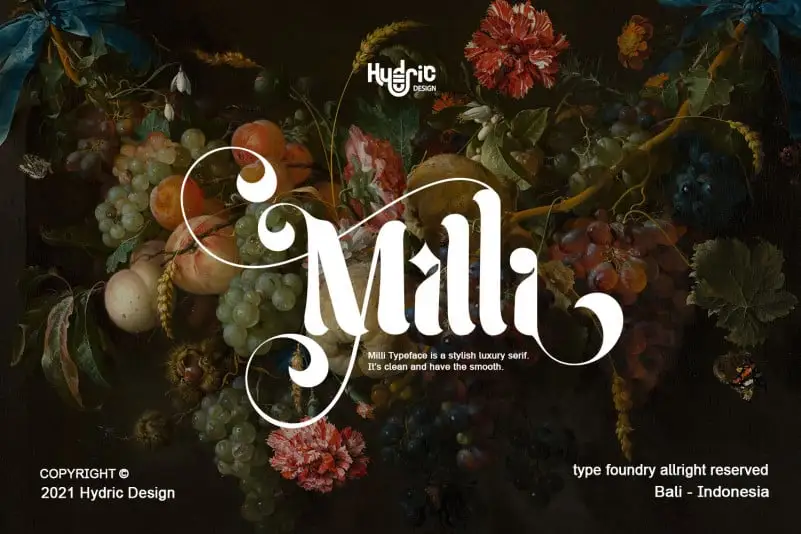
Milli Display Typeface – Download Grátis
A Milli Display Typeface é uma serif moderna e elegante que transmite sofisticação para qualquer projeto. Com sua aparência limpa e linhas finas, esta fonte representa um estilo de letra clássico com um toque atualizado. O estilo serifado da família de letras oferece movimentos sutis e fluidos, enquanto também mantém uma personalidade alegre e versátil que é capaz de variar inúmeras formas elegantes. Este tipo de fonte contém mais de 40 ligaturas para garantir um acabamento perfeito em cada palavra ou frase. Além disso, possui cerca de 100 alternativas para letras, permitindo uma variedade infinita de curvas e formas bonitas que pode ser introduzida em apenas segundos. A HydricDesign traz o luxo dos estilos serif clássicos ao formato moderno da fonte tipo, ideal para ambientes visuais sofisticados e criativos.